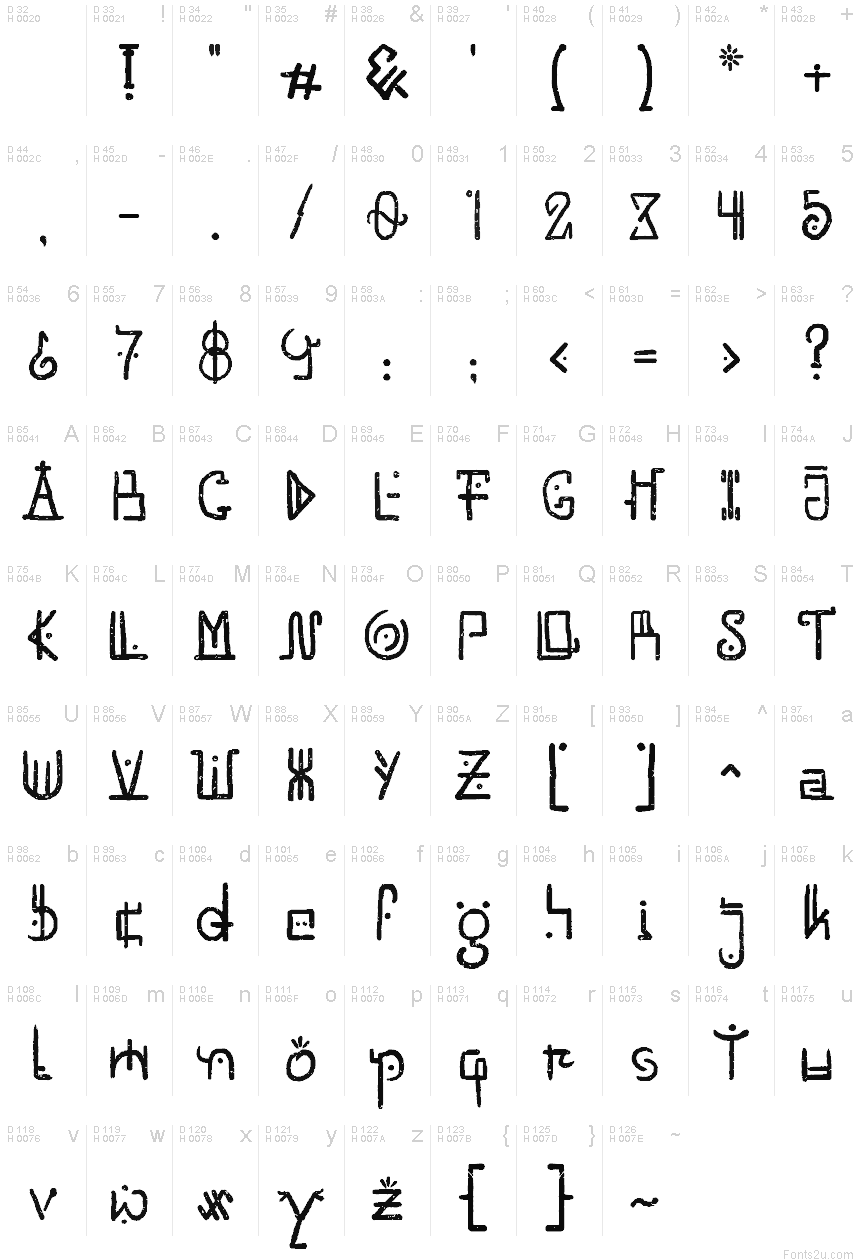
Unai Native Native
A equipe responsvel pela Unai foi alm da criao de uma fonte, eles criaram uma famlia! Na verdade, uma tribo, como a equipe prefere. A Unai foi concebida aps o desenvolvimento de uma lista de conceitos e assuntos de interesse comum. A partir da eles mergulharam em uma pesquisa complexa em que foram explorados de sistemas de escrita de comunidades nativas pr-colombianas at uma relao com uma esttica referente a seres extraterrenos. O resultado uma famlia rstica e muito bela, com uma quantidade boa de aplicaes possveis. A Native a verso inicial, texturizada. A Regular possui desenho semelhante a Native mas sem as ranhuras. Por fim, a Lines prope uma verso light da fonte.
OBS: Fonte desenvolvida como trabalho final para a disciplina de Experimentos em Tipografia Digital sob a orientao do prof. Eduardo Novais.